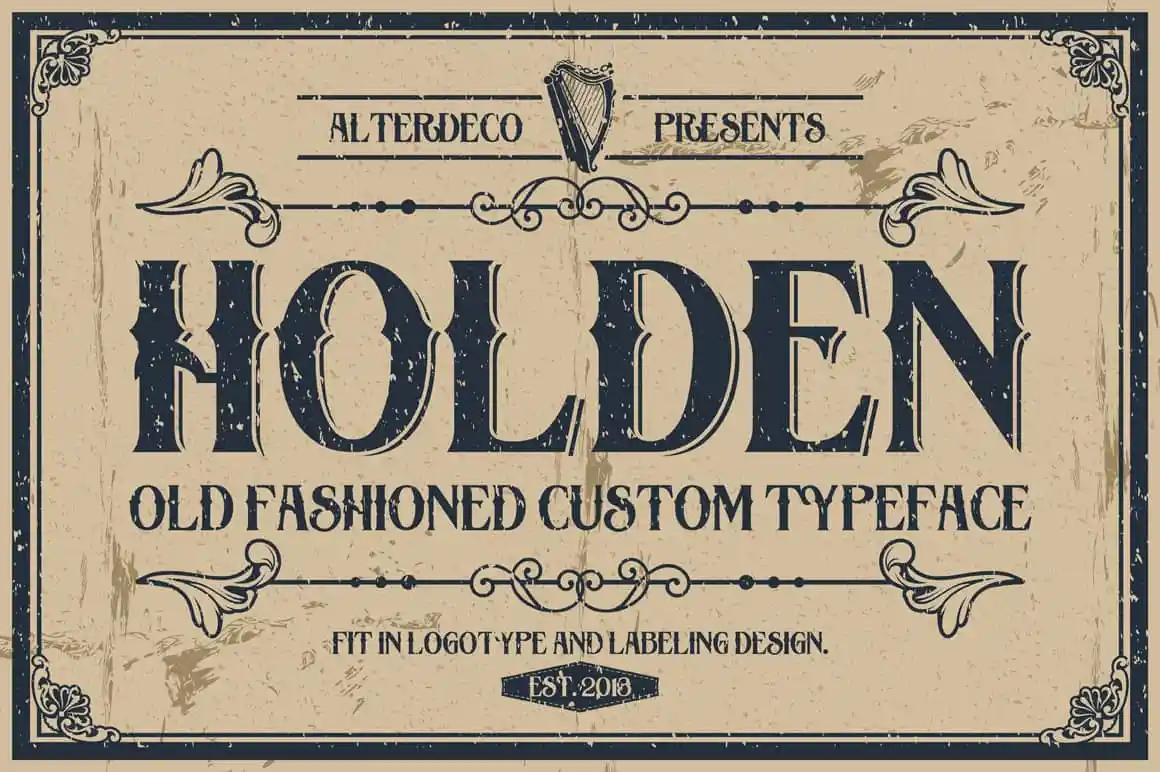
Holden Typeface – Fonte Grátis
Holden Typeface
Descubra Holden Typeface neste download exclusivo, uma revisão do estilo vintage que reviverá os dias nostalgicos dos anos 50 e 60. Proposta para designers de moda que buscam um toque retro em suas criações de roupas, Holden é perfeito tanto para logotipos quanto para rótulos. Suas letras maiúsculas têm o charme suave da tipografia em estilo sombreado. Disponível nas versões OTF e TTF, este fonte Display é uma aposta segura para qualquer projeto de design que desejou um olhar nostálgico, repleto de sofisticação e elegância. Que tal revitalizar sua identidade visual com esse charmoso revival do passado? Descubra Holden Typeface hoje mesmo!